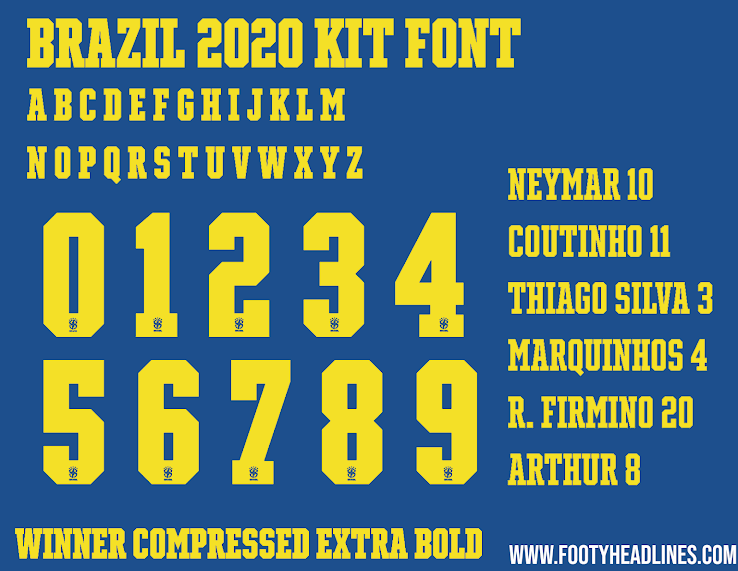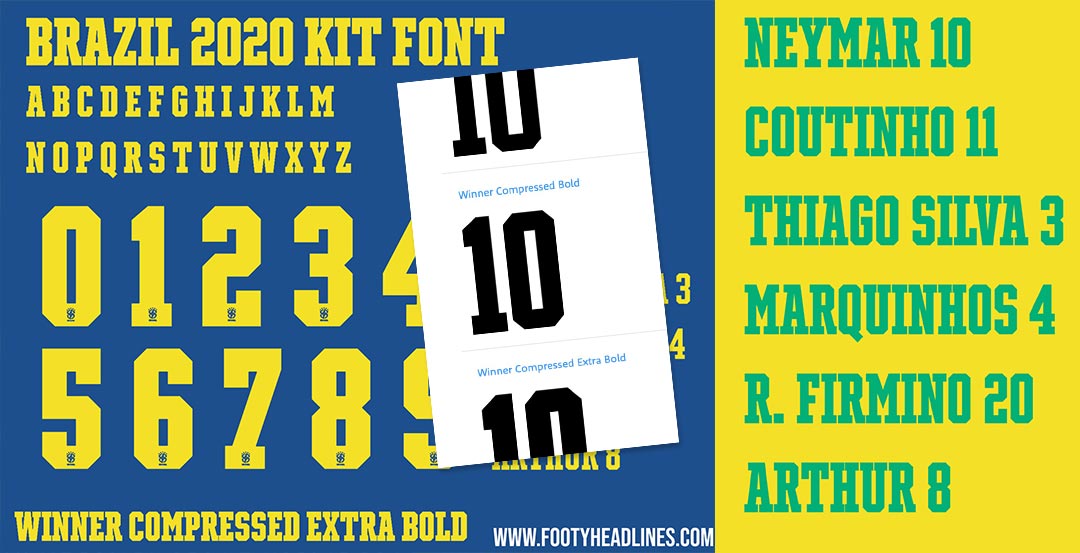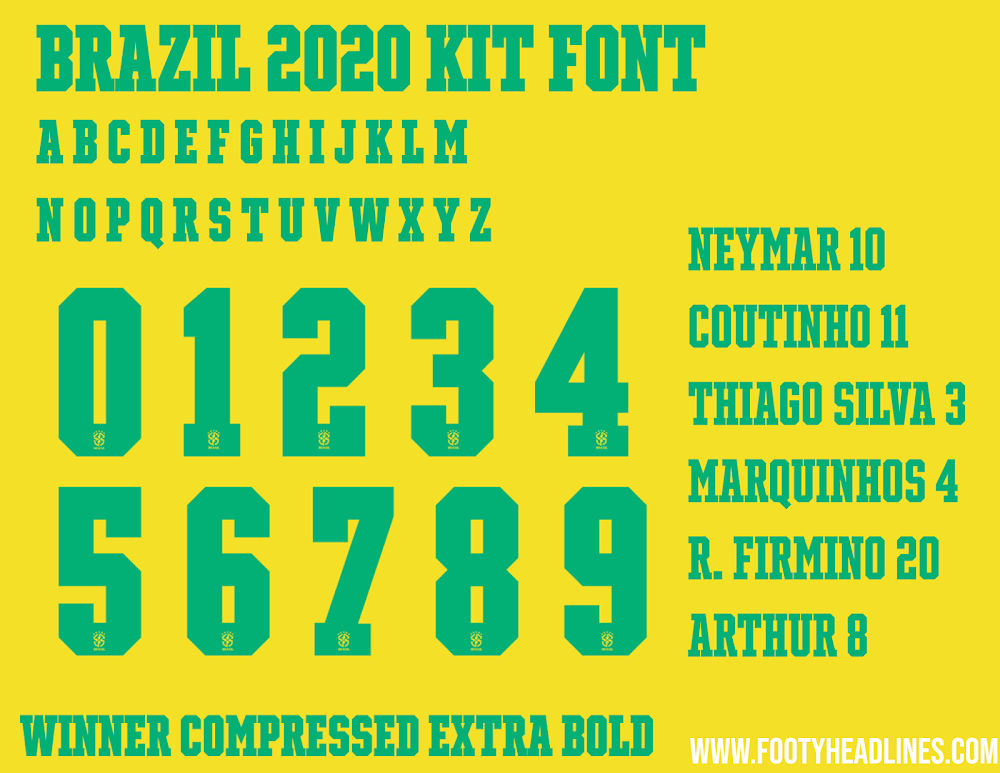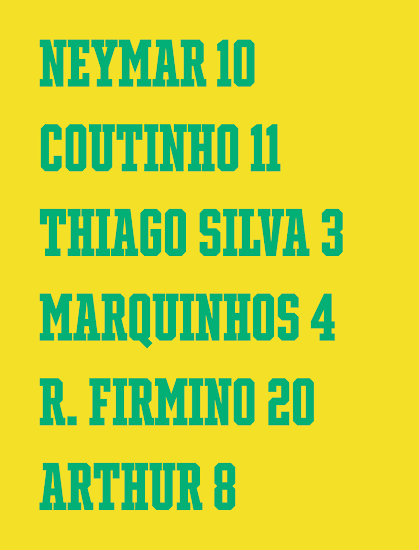
Eigentlich auf Standardschriftart basierend: 1970-inspirierte Nike Brasilien 2020 Trikot Schriftart enthüllt - Zwei Trikot-Macher & Schriftarten 1970?!
Update: Die Brazil 2020 Trikot Schriftart ist eigentlich nicht für Brasilien maßgeschneidert, sondern die Standardschriftart "Winner Compressed Bold" (entworfen von @sportsfonts_com). Wir haben eine Schriftvorschau der Trikot-Schriftart "Brasilien 2020" erstellt, um euch einen Blick auf alle Zahlen und Buchstaben sowie einige Spielerbeispiele zu liefern. Zuvor wurde nur die Nr. 10 der Trikot-Schriftart "Brasilien 2020" angezeigt.
Die Nike Brasilien 2020 Trikots kommen mit einer exklusiven Trikot-Schrift für die brasilianische Nationalmannschaft, die der Weltmeisterschaft 1970 Tribut zollt, genau wie die Trikots.
Nike Brasilien 2020 Trikot Schriftart
Die Schriftart für das Nike Brasilien 2020-Trikot hat ein bemerkenswertes klassisches Design, das sich eng an die Schriftart der Weltmeisterschaft 1970 anlehnt. Nike's Bild enthält keine Namen, aber das wird sich in den offiziellen Spielen ändern.
Die Schriftart "Brasilien 2020 Weltmeisterschaft" ist eigentlich die gleiche wie die reguläre Schriftart "Winner Compressed Bold".
Es gibt da eine etwas seltsame Sache mit den Brazil 1970 Shirts und ihren Nummern. Brasilien "hatte 1970 zwei verschiedene Hemdenhersteller" - Athleta und Umbro, die unterschiedliche Schriftarten benutzten.
Brasiliens Trikot-Schriftart ist inspiriert von der Trikot-Schriftart, die Athleta für die brasilianischen Trikots von 1970 verwendet hat. Die Umbro-Brasilienbausätze von 1970 enthielten eine andere Schriftart (über Mantos do Futebol).
Auf dem von Pel getragenen Trikot, das im Museu do Futebol im Pacaembu-Stadion in So Paulo ausgestellt ist, ist das Etikett von Umbro zu sehen, zusammen mit der Nummer im runden Stil.
Das Logo der brasilianischen Fußballkonföderation befindet sich auf der Unterseite der Nike Brasilien 2020-Trikotnummern.
Die Schriftart für das Nike Brasilien 2020 Trikot wird diesen Monat zusammen mit dem Trikot in der WM-Qualifikation 2022 debütieren.